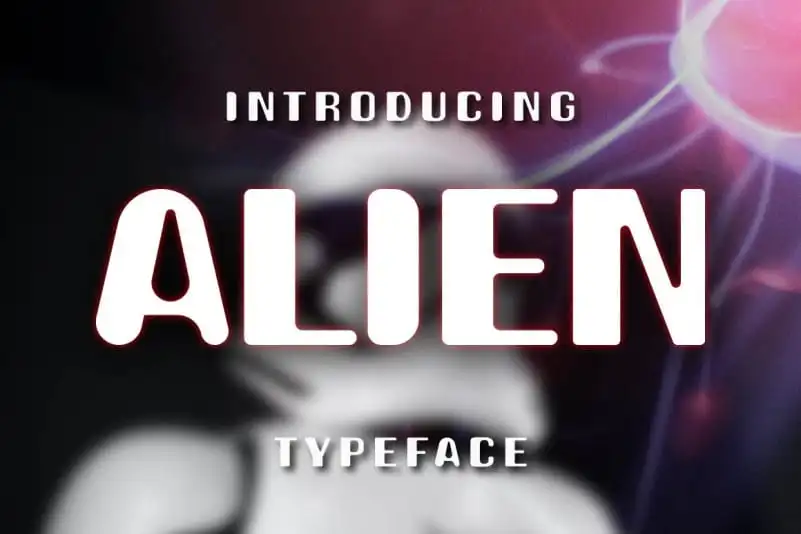
Alien Display Font – Download Grátis
A Alien Display Font é uma escolha perfeita para quem procura uma fonte de display audível e inovadora. Desenvolvida por WNGSTD, esta tipografia abraça o conceito futurista enquanto mantém um tom autêntico. Com linhas fortes e acentos modernos, ela destaca-se como uma opção elegante para projetos digitais que exigem notoriedade. Se você está buscando dar à sua criação aquela pitada inconfundível de originalidade na era digital, a Alien Display Font é um passo a frente no caminho da criatividade. Composta para manter seu design distintivo e destacá-lo do resto, esta fonte é uma verdadeira pedra angular em qualquer projeto visual contemporâneo.
Designer: WNGSTD